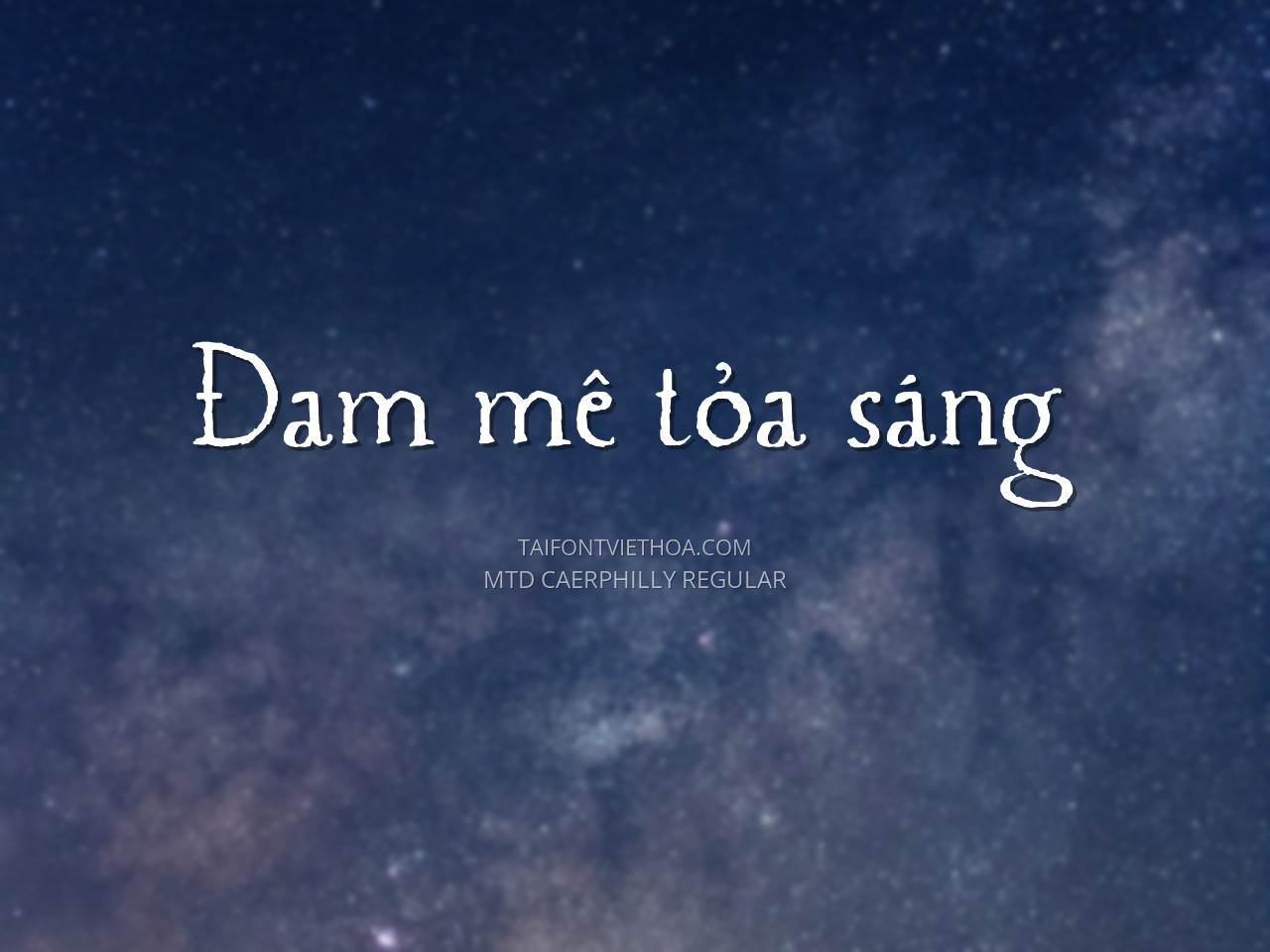
Font việt hóa MTD Caerphilly Regular
Giới thiệu về font Caerphilly Regular – Nét cổ điển đậm chất Anh Quốc
Caerphilly Regular là một kiểu chữ serif mang hơi hướng cổ điển phương Tây, được đặt theo tên của thị trấn Caerphilly nổi tiếng tại xứ Wales, Anh Quốc. Dù không công bố rõ tác giả, font thường xuất hiện trong các bộ sưu tập mang đậm phong cách retro, dùng cho in ấn, biên tập sách, poster sân khấu và các sản phẩm truyền thông đậm tính truyền thống. Với cấu trúc vững chắc, chân chữ rõ ràng và các chi tiết mang nét hoài cổ, Caerphilly Regular đem lại cảm giác lịch thiệp, trang trọng và phù hợp với các nội dung cần độ tin cậy cao.
Đặc điểm thiết kế và ứng dụng thực tiễn của Caerphilly Regular
Font Caerphilly Regular thuộc nhóm serif (có chân), với thiết kế rõ ràng, độ dày ổn định và chân chữ sắc nét. Các ký tự được tạo hình cân đối, mang đến sự nghiêm túc nhưng không kém phần nghệ thuật. Phù hợp để trình bày nội dung dài trong các sản phẩm biên tập hoặc làm tiêu đề cho những ấn phẩm truyền thống. Bên cạnh đó, font cũng sở hữu khả năng tạo điểm nhấn khi sử dụng với kích thước lớn trong poster hoặc bảng hiệu sự kiện mang tính lịch sử, giáo dục hoặc văn hóa.
Caerphilly Regular là lựa chọn lý tưởng cho các thiết kế bìa sách, tiêu đề báo, logo trường học, thương hiệu truyền thống, bao bì sản phẩm cổ điển, hoặc thư mời sự kiện trang trọng. Ngành nghề phù hợp bao gồm: xuất bản, giáo dục, lịch sử, văn hóa – nghệ thuật, bất động sản cao cấp hoặc tổ chức sự kiện có yếu tố truyền thống.